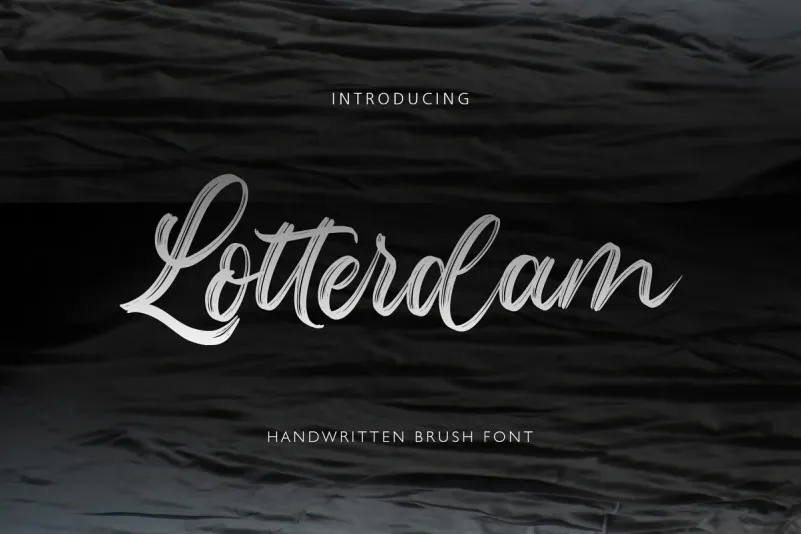
A Lotterdam Font é uma escolha perfeita para quem procura uma fonte script moderna e despojada. Ela foi criada pela Rochart e traz um estilo fresco de pintura, ideal para criar logotipos, artes digitais de escrita a mão, design de marca e signos. Esta fonte é especialmente adaptada para ambientes limpos e clean, sem excessos, que buscam uma transparência e sofisticação ao mesmo tempo. Seja para aplicativos em redes sociais ou materiais promocionais, a Lotterdam tem tudo o que você precisa para dar um toque moderno e autêntico aos seus projetos digitais. Através da sua textura elegante e estilo casual, esta fonte oferece uma maneira única de expressar seu design no mercado atual. Não espere mais – instale a Lotterdam Font e veja como ela transforma suas ideias em realidade.